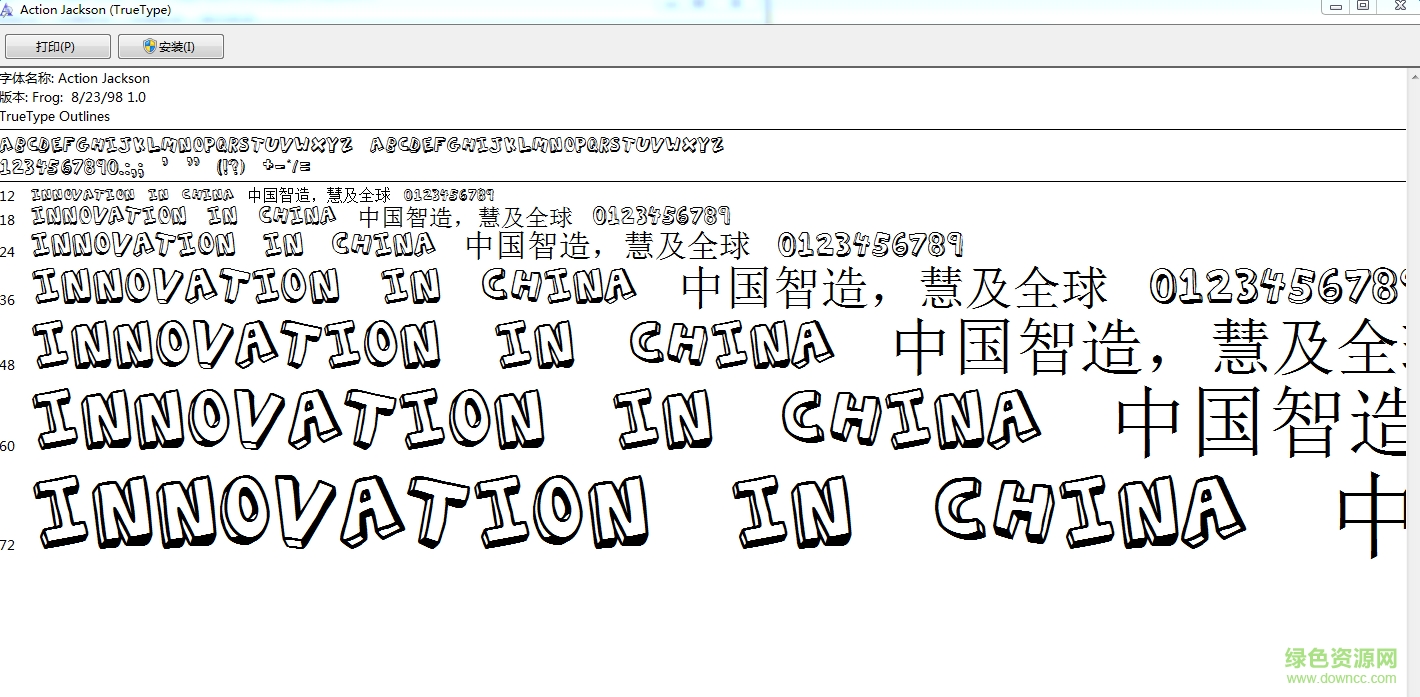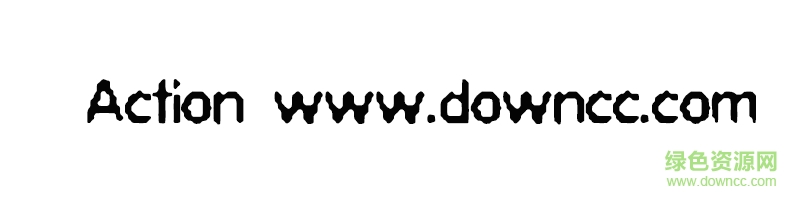
Action字體是一款A(yù)ction風(fēng)格英文字體軟件,Action風(fēng)格的字體給人非常放松的感覺,深受廣大年輕人的喜愛,還有更多好看字體盡情期待,歡迎到綠色資源網(wǎng)下載體驗(yàn)!
Action是一款A(yù)ction風(fēng)格英文字體,字體效果比較放松,喜歡英文體字的朋友可以下載使用看看效果如何。